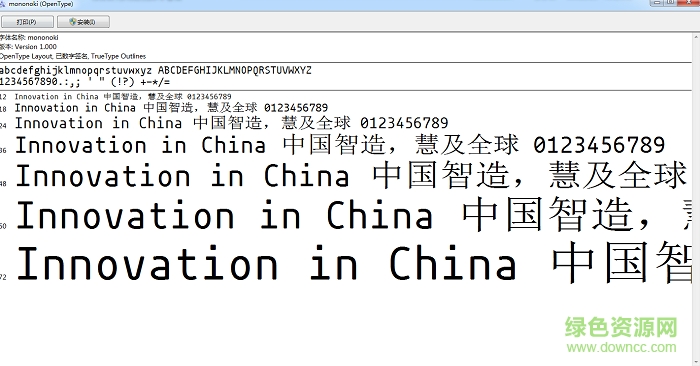
mononoki
mononoki字體是一款適合在電腦屏幕上使用的等寬編程字體,擁有超高辨識(shí)度,外形清晰美觀,且附帶有詳細(xì)的mononoki字體安裝方法,需要的朋友快來下載吧!
Mononoki字體特點(diǎn)
專為編程設(shè)計(jì)的 Mononoki 是一款英文等寬字體,簡(jiǎn)潔大方,號(hào)稱可讀性和辨識(shí)性強(qiáng),在高分辨率和低分辨率下表現(xiàn)都非常穩(wěn)定,不易產(chǎn)生視覺疲勞。
Mononoki 字體內(nèi)容